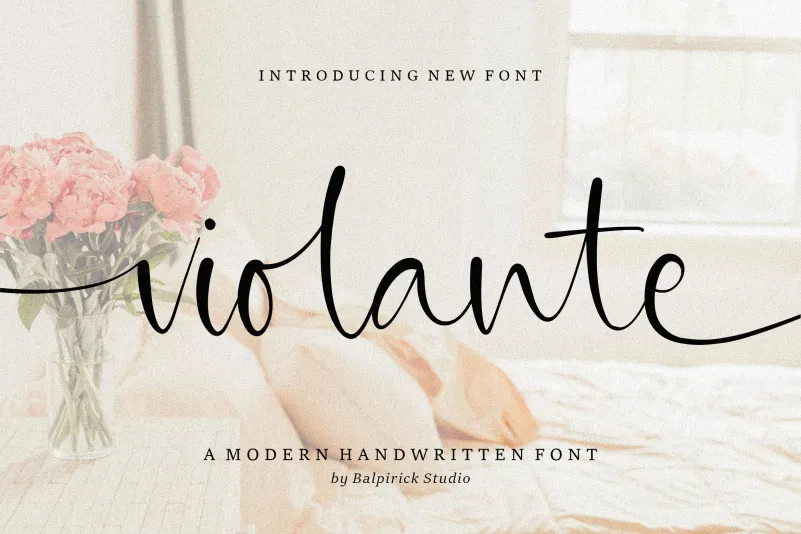
Violante Calligraphy Font – Download Grátis
A violante Calligraphy Font é perfeitamente adaptada para diversas categorias de uso, incluindo embalagens de produtos, projetos de marca, revistas, mídia social, casamentos e até mesmo utilização casual para destacar frases sobre fundo. Suas linhas delicadas e escrita a mão criam um efeito elegante que se assemelha ao estilo autêntico das letras cursivas, tornando-a uma escolha perfeita para estilos que valorizam o detalhe e a sofisticação. Com seu designer balpirick dedicado, esta fonte oferece a oportunidade de personalizar a sua identidade visual de maneira única. Suas sutilezas e nuances são ideais para criar um registro impecável e único para marcas, embalagens ou qualquer conteúdo que deseje destacar através da escrita criativa. Seja você uma marca profissional buscam adicionar um toque especial a suas campanhas de mídia social ou casamentos, ou simplesmente aquele designer desejando dar mais vida à sua arte visual com uma letra delicada e elegante, Violante é sem dúvida um recurso indispensável para seu arsenal criativo.